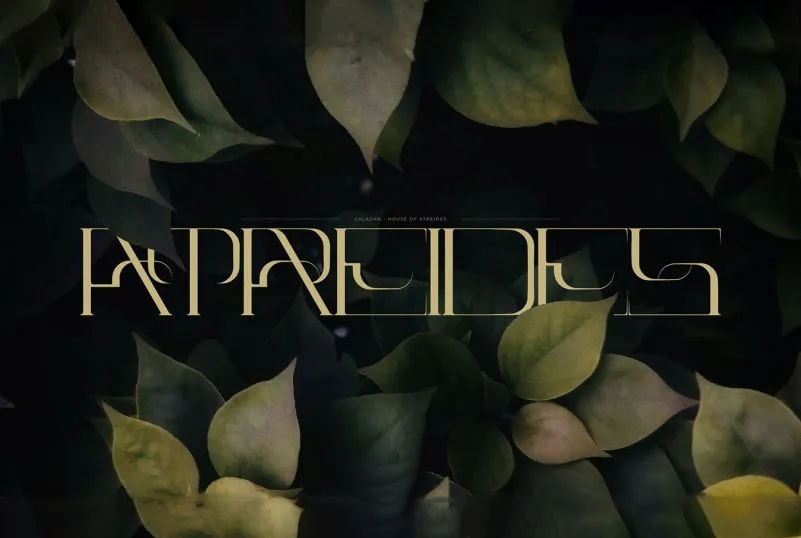
A Atreides Font é uma elegante e moderna fonte de display que traz uma personalidade única aos designs, tornando-a ideal para temas minimalistas e contemporâneos. Suas linhas sólidas e formas arredondadas dão ao texto um aspecto sofisticado e funcional. Com suas linhas retas e leves, a Atreides é perfeita para aplicar em diversas áreas do design gráfico, incluindo headlines, logos, cartazes, embalagens de produtos ou mesmo as camisetas dos seus clientes. Suas formas geométricas proporcionam um estilo minimalista que destaca seu uso em ambientes comerciais como lojas de café, restaurantes e cafés. Além disso, ela encaixa perfeitamente nas cabeças-de-pagina de revistas ou nos cartões-postais de uma marca. A Atreides também é ótima para cartazes publicitários e até mesmo para eventos casuais como festas e cerimônias de casamento. Com uma abordagem minimalista, ela combina perfeitamente com a atmosfera contemporânea da vida moderna no Brasil, tornando-se um recurso gráfico versátil e irresistivelmente atraente.